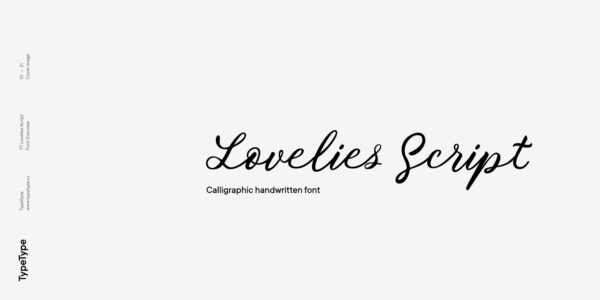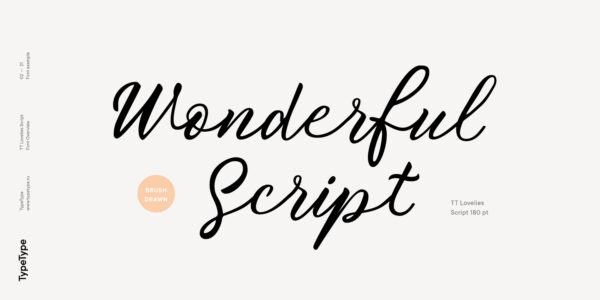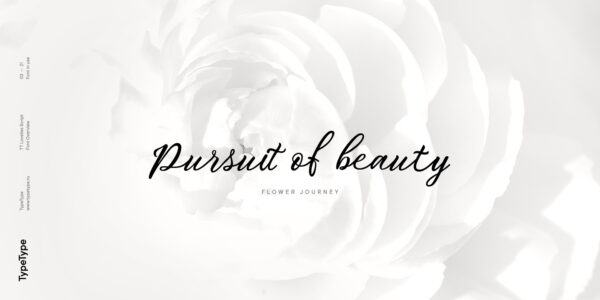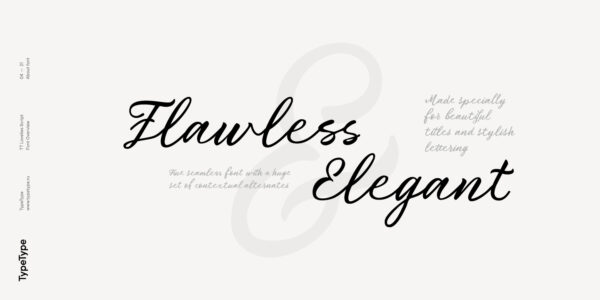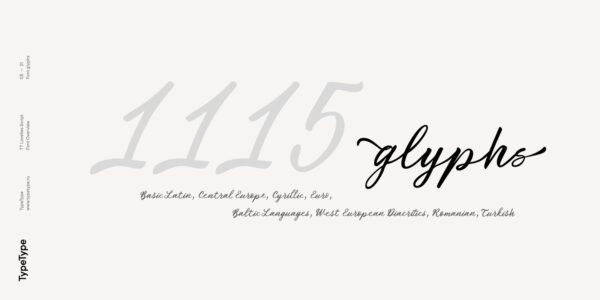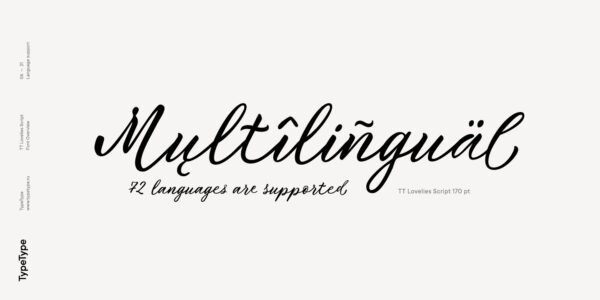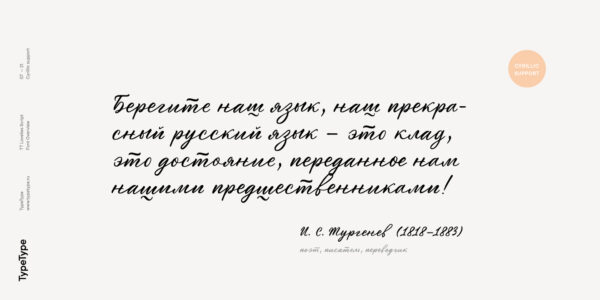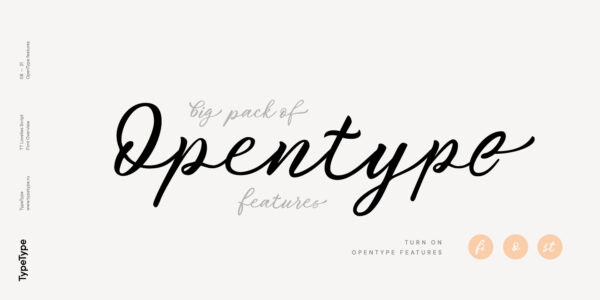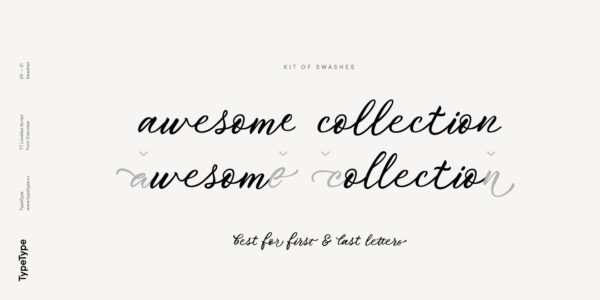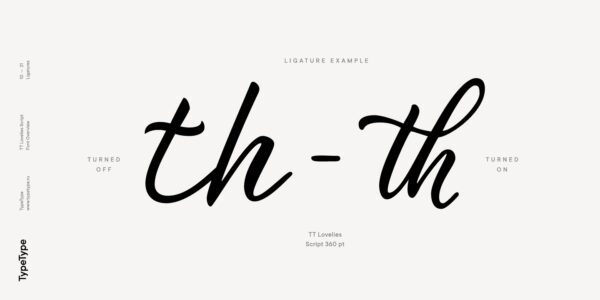
TT Lovelies Script
TT Lovelies Script — ТТ Лавлиз Скрипт
Произносится «ТТ Лавлиз Скрипт». «Lovelies» — производное слово от lovely, в переводе с английского «прекрасный», «Script» — в переводе «письмо» . Буквы «TT» являются аббревиатурой названия компании.
TT Lovelies Script — рукописный шрифт с уникальным беспрерывным рисунком, основанный на авторской каллиграфии.
О гарнитуре TT Lovelies Script
Без ложной скромности можем сказать, что TT Lovelies Script является одним из самых сложных проектов, который мы когда-либо выполняли. 1115 глифов, более 2000 контекстных альтернатив, 10 000 пар кернинга, а также большое количество OT features, включая лигатуры и минускульные цифры. Главная отличительная особенность шрифта — настоящая беспрерывность.
Мы сделали невозможное: в TT Lovelies Script даже прописные буквы соединяются со строчными во всех случаях без разрывов. За основу шрифта взята авторская каллиграфия российского дизайнера Алены Коробановой, которая путем кропотливого труда превратилась из красивого почерка в полнофункциональный шрифт. TT Lovelies Script является очень живым и игривым шрифтом с небольшими нюансами непредсказуемости.
Включите использование OT features CALT & DLIG в вашем графическом редакторе и используйте шрифт на полную мощность. Каждая строчная буква имеет характерные росчерки, начинающие и заканчивающие слово. Росчерки включаются автоматически при наборе двух дефисов в начале и конце слов соответственно. Например, напишите — — apricot — — и вы получите красивые росчерки в начале и конце слова.
TT Lovelies Script использует огромное количество контекстных альтернатив и лигатур, которые помогают поддерживать ощущение рукописности. Для каждой буквы нарисована отдельная форма графемы для конца строки, а для удобства работы с прописными знаками мы интегрировали CaseSensitive OT feature. Также для работы с цифрами мы включили: onum, sups, sinf, numr, dnom, frac, ordn. Чтобы воспользоваться всеми этими прекрасными опциями вы должны использовать программы, которые поддерживают OT features.